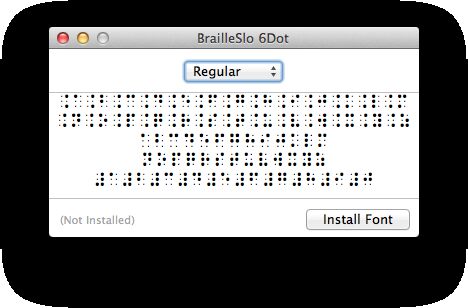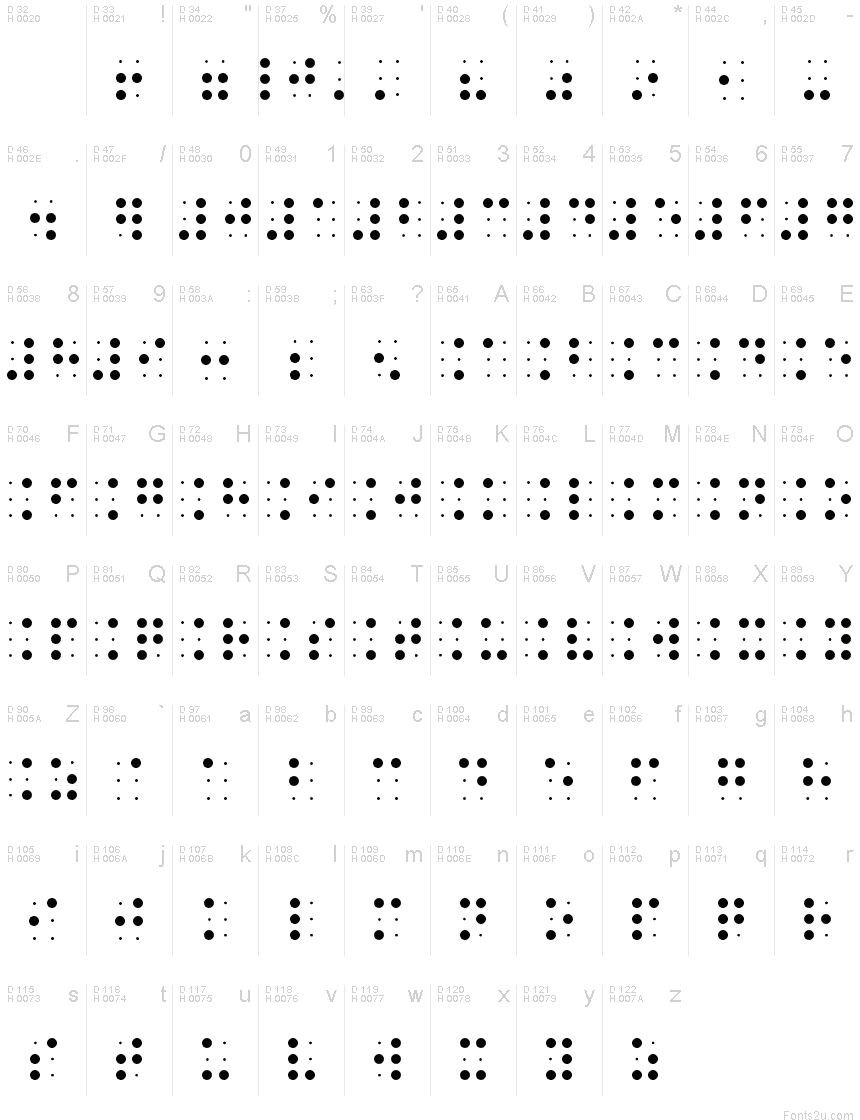
BrailleSlo 6Dot
Slovenian braille - font used by the blind and the visually impaired.
Pri uporabi te tipografije upotevajte naslednja opozorila:
* Pri pravilnem esttočkovnem brajevem zapisu se uporabljajo določena pravila zapisovanja znakov, vendar al vseh pri avtomatični spremembi fontov ni mogoče upotevati (na primer pri zapisovanju večmestnih tevil, kratic, začetnih in končih narekovajev, ...).
* V letu 2016 je prilo do posodobitve slovenske brajice. 6-točkovni brajevi fonti ne upotevajo teh posodobitev. Standard posodobljene esttočkovne brajice je objavljen na spletni strani Komisije za slovensko brajico - http://brajica.splet.arnes.si/
* 6-točkovni brajevi fonti niso primerni za reliefni tisk.